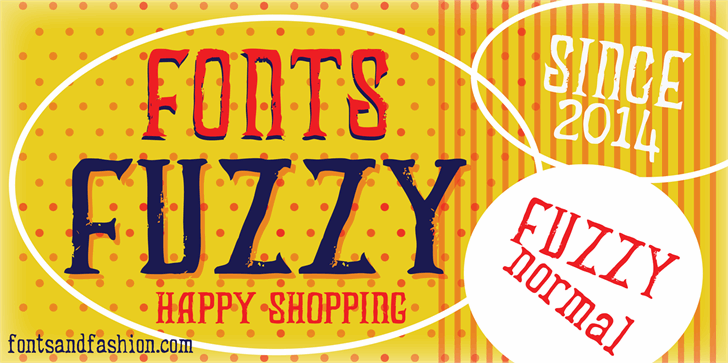
Aqui está uma descrição envolvente para a página de download da fonte “FUZZY bold”, categorizada como Display Fonts: Esta fonte “FUZZY bold” é um adorável desafio contra a ordem tradicional, repleta de ondulações e estímulos visuais que te fazem pensar em algo não-linear e vibrante. Seu designer, Hamilton, tem a habilidade única de criar uma fonte que vai mais além do texto, trazendo vida para qualquer design. Embora seja classificada como um Fontes Display (não confundir com Fonts Sans-serif ou Serifs), “FUZZY bold” é perfeita para incorporar em artigos gráficos onde você deseja destacar o estilo. Seu design desenfreado e colorido captura a atenção instantaneamente. Para adquirir a fonte completa, visite http://fontsandfashion.com/fonts/fuzzycollege-deptworn. Não se esqueça de seguir eles nas redes sociais: FACEBOOK e PINTEREST. E para explorar ainda mais fonts no mesmo estilo, veja a conta do Fontspace criada por Fonts and Fashion. Obrigado por apreciar este recurso gráfico. Seja criativo!